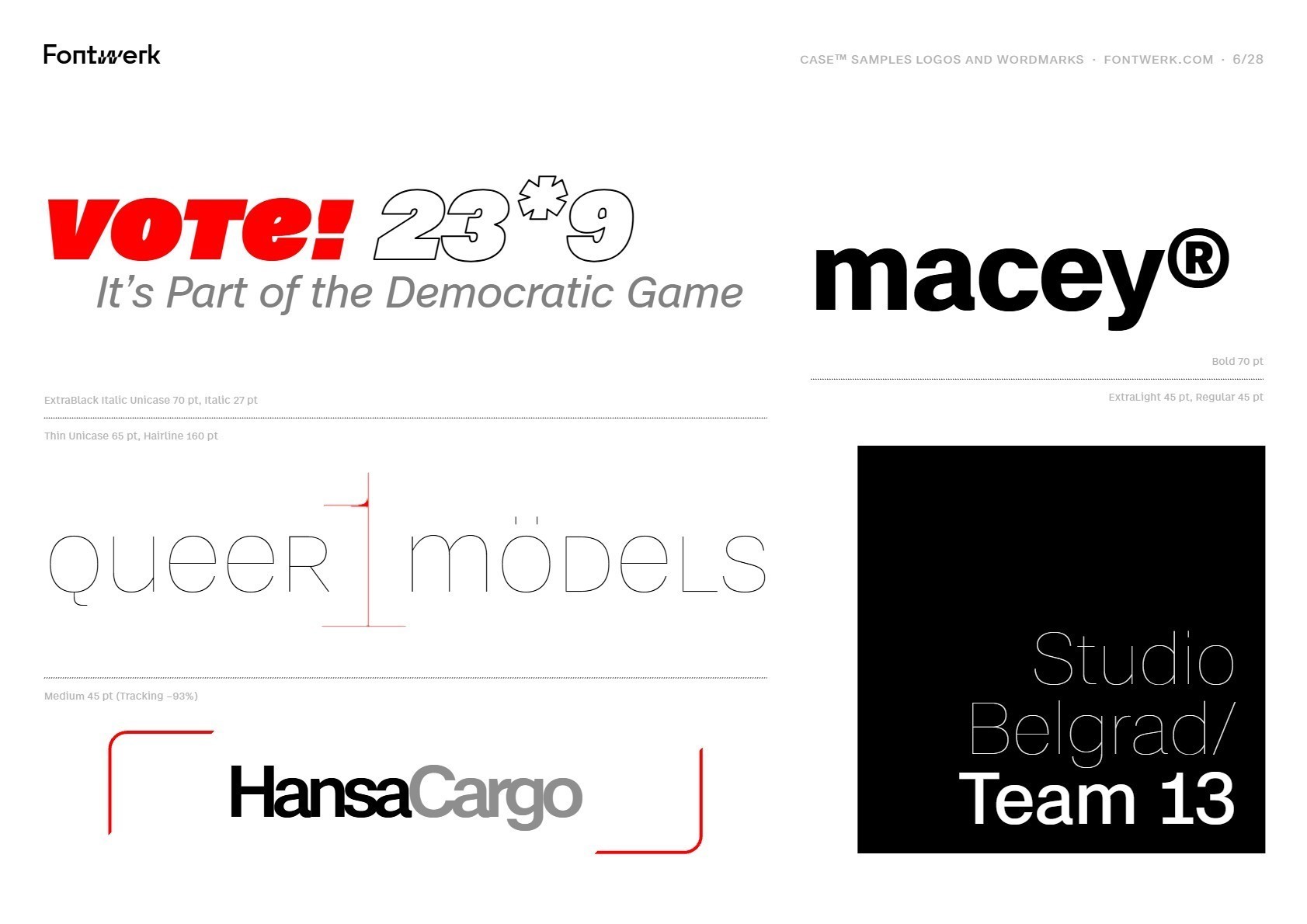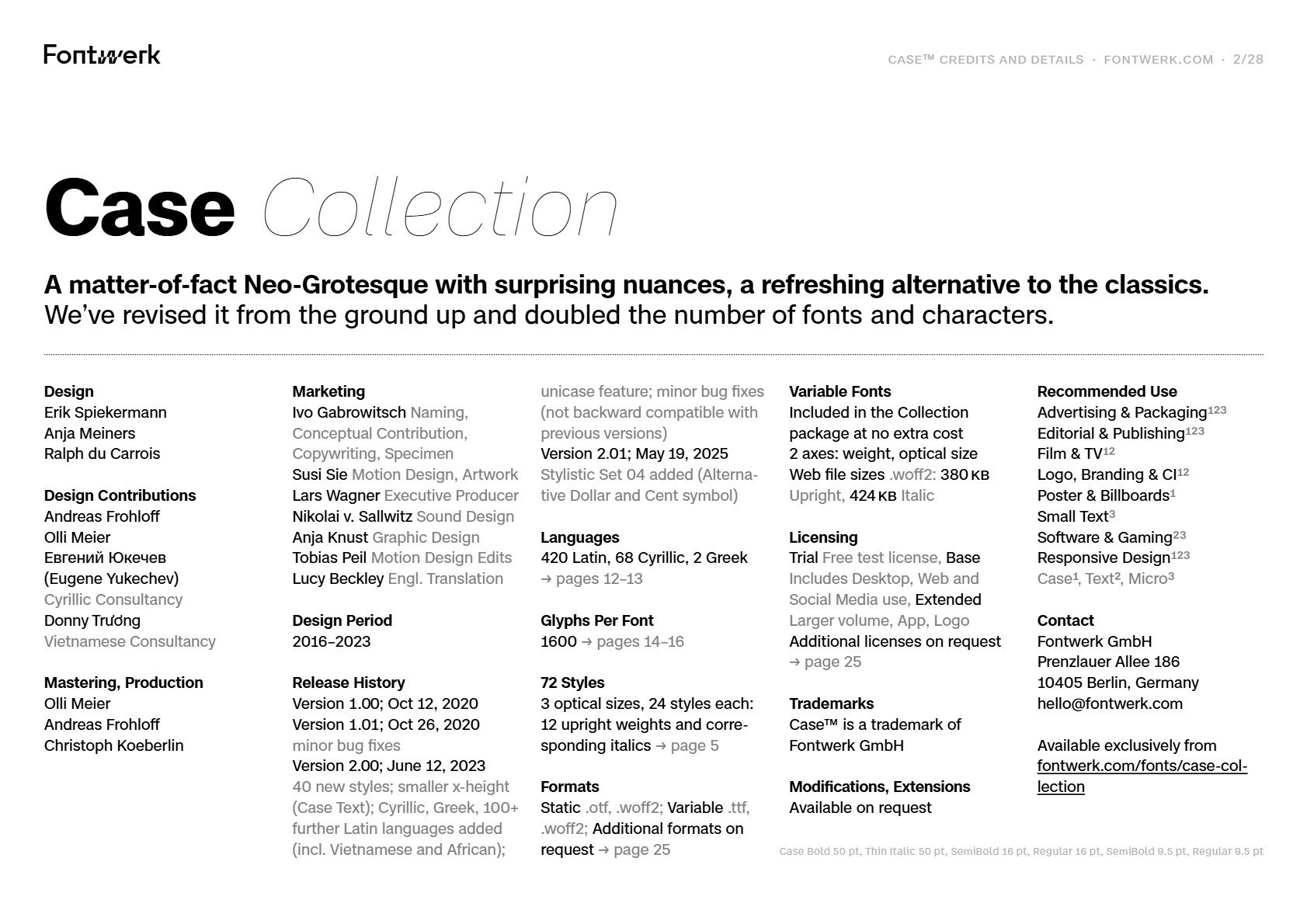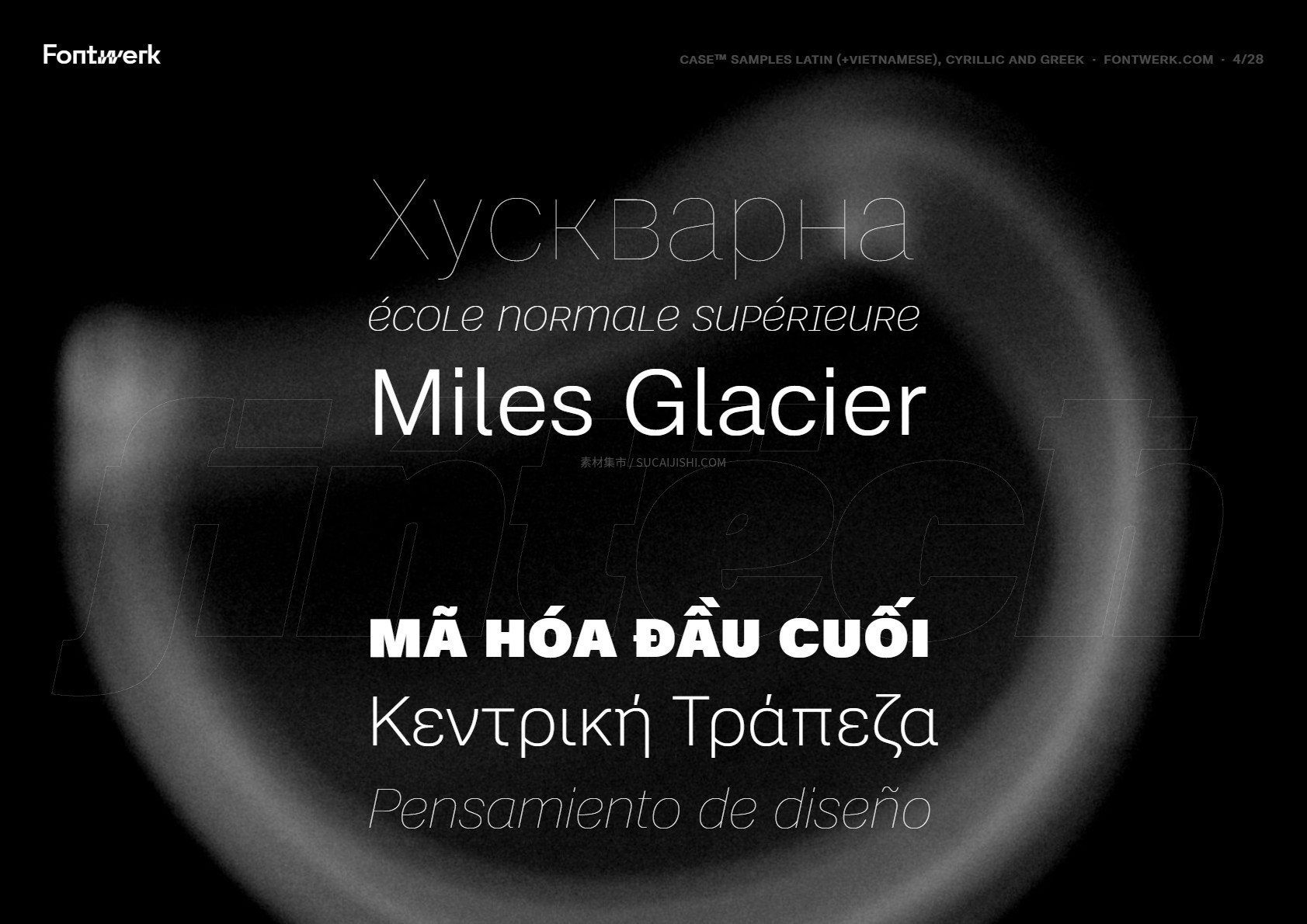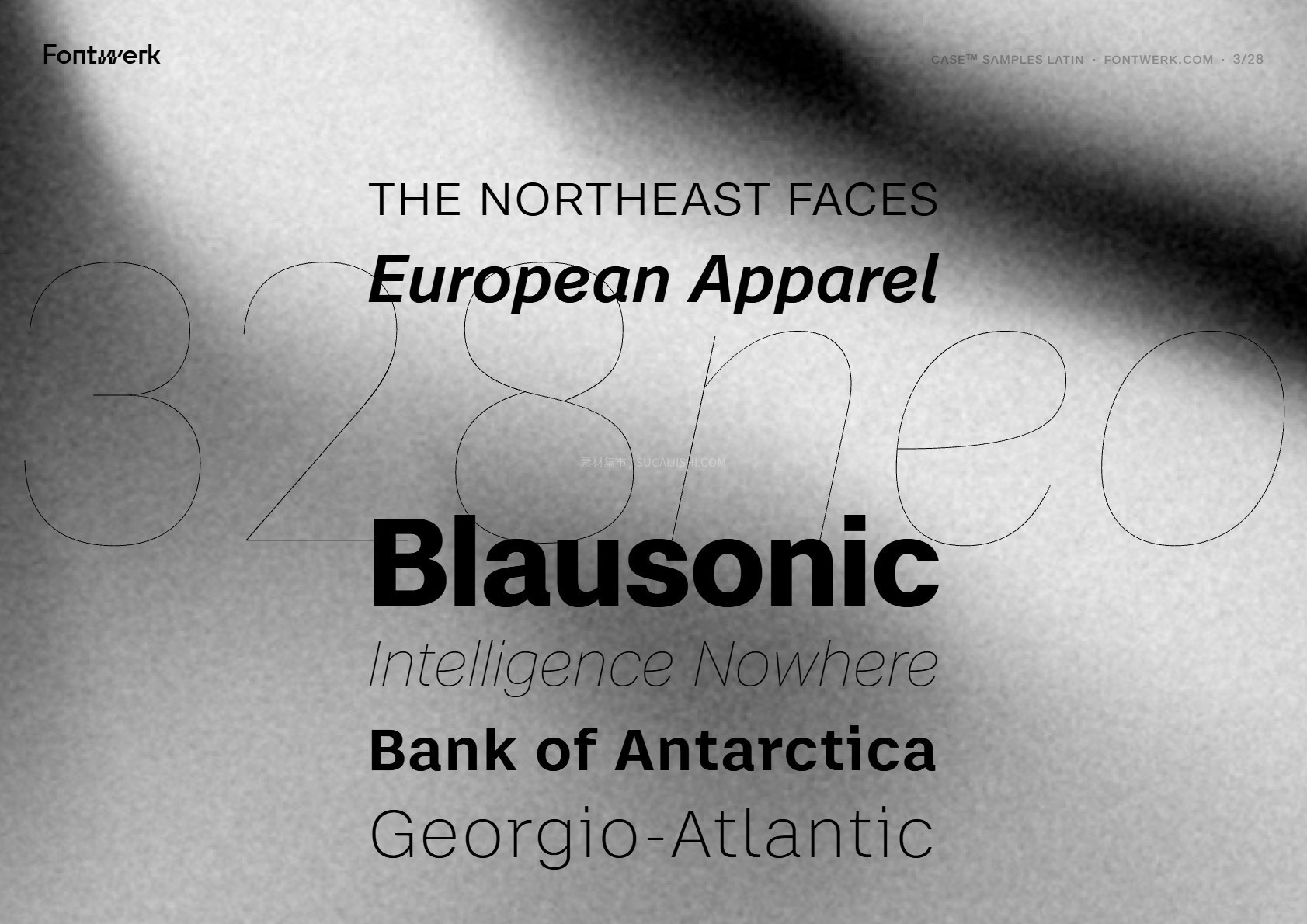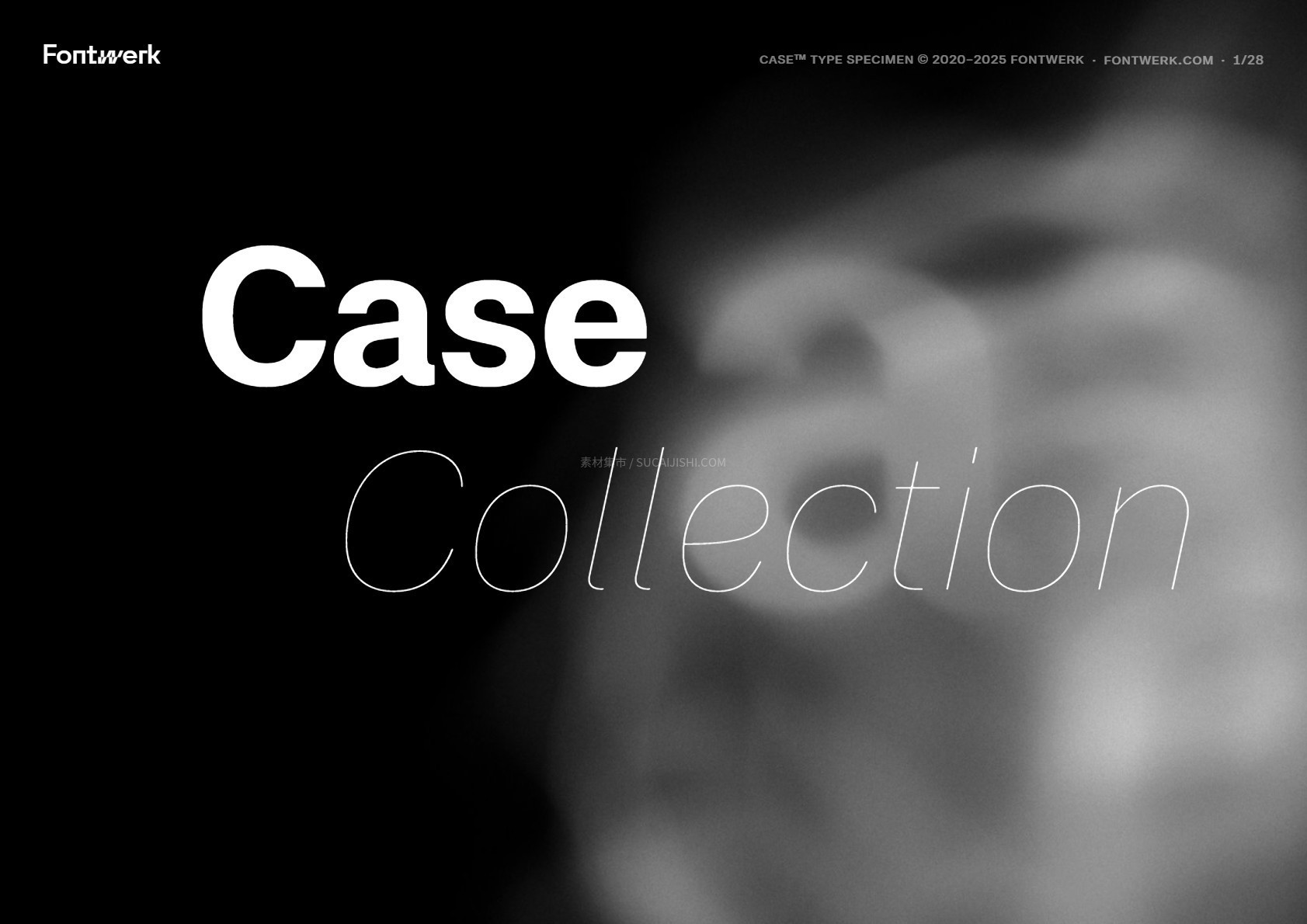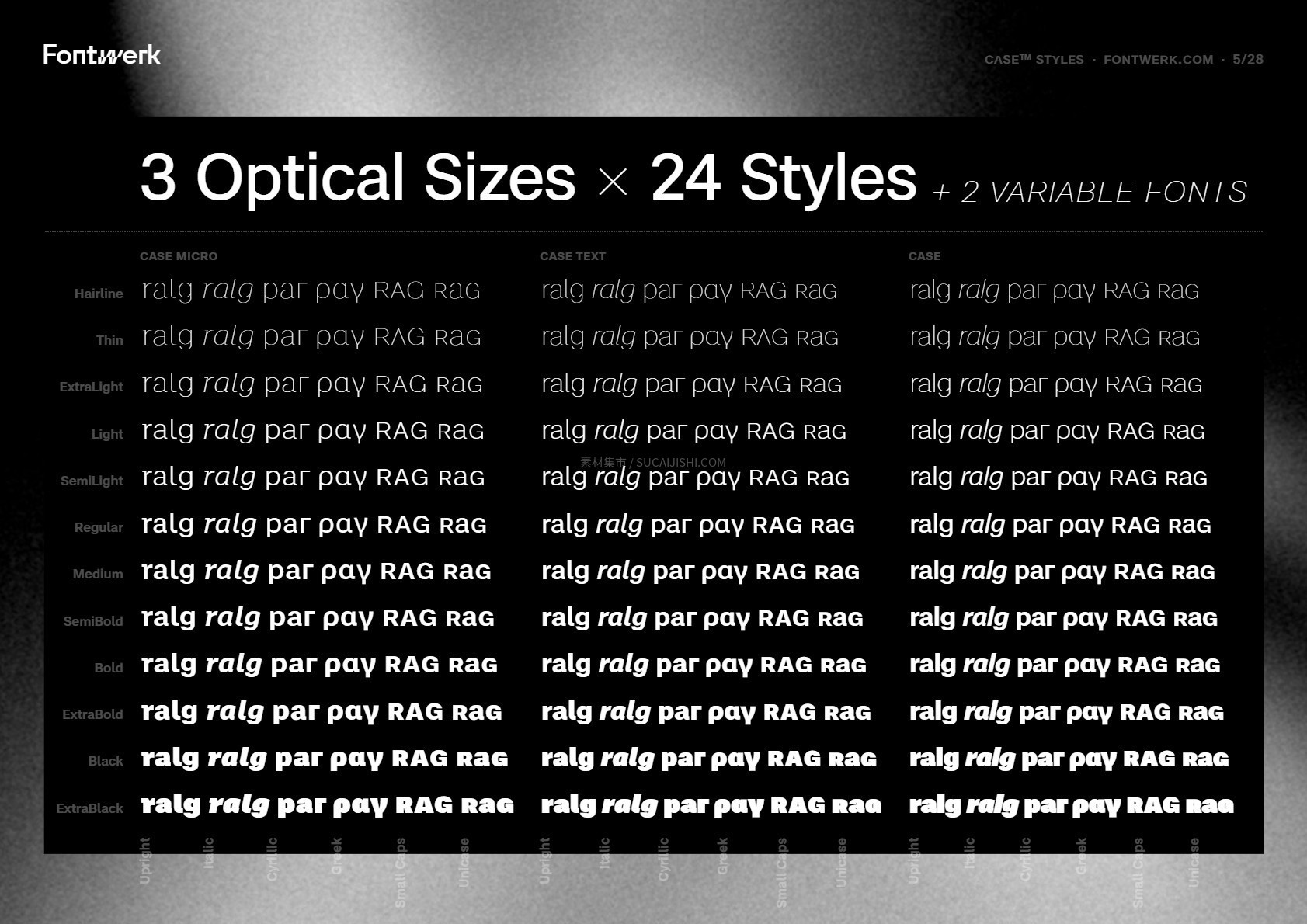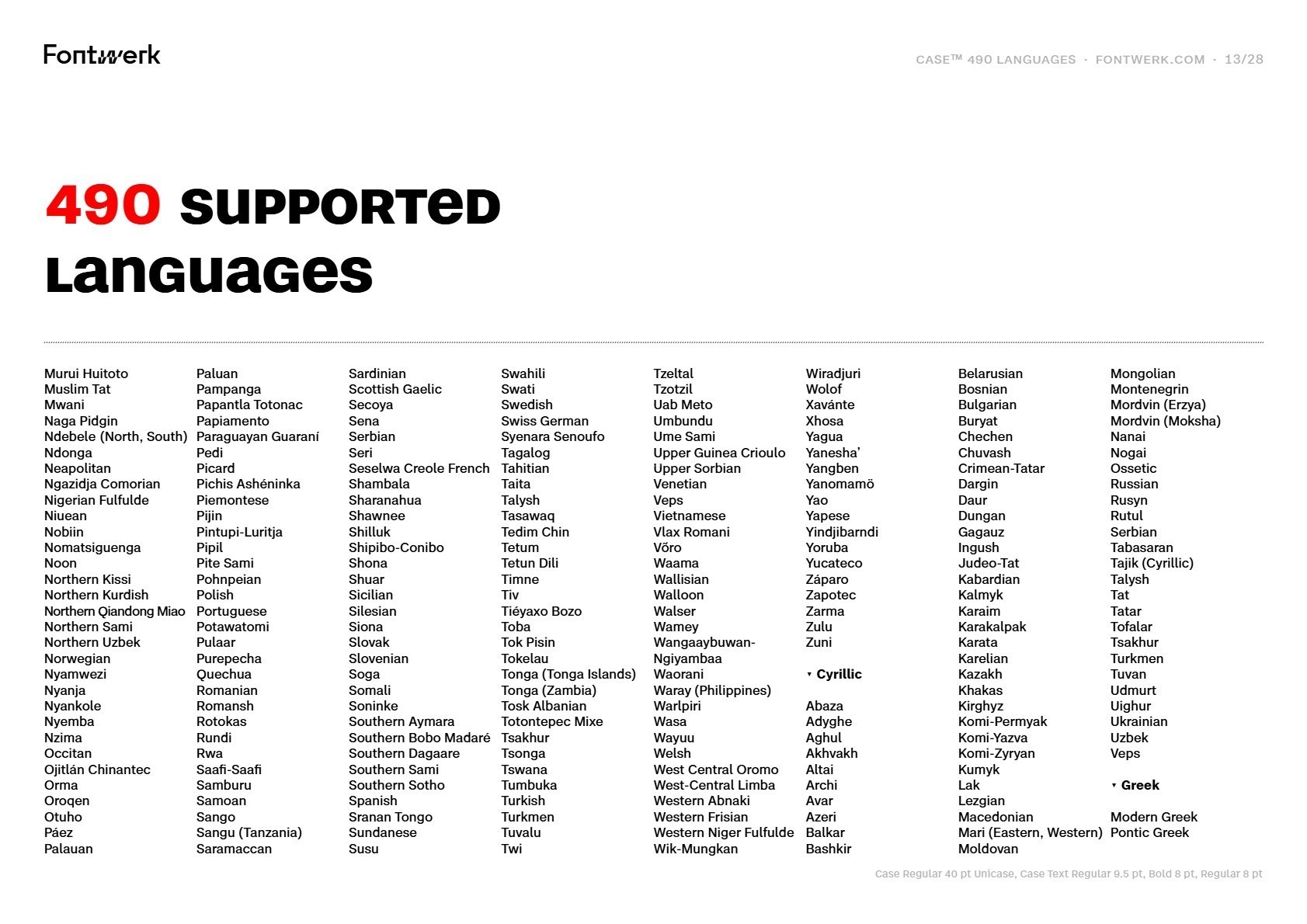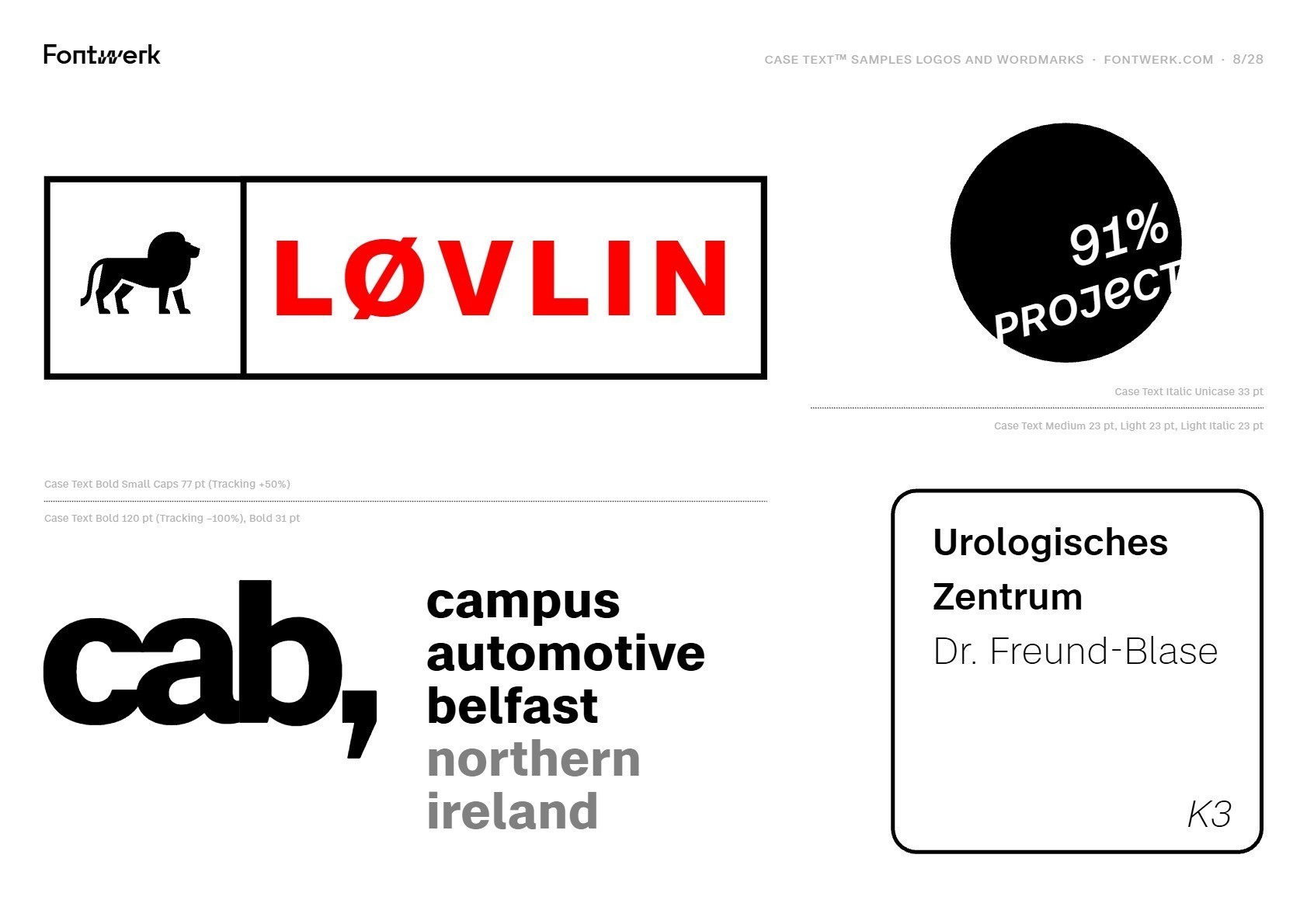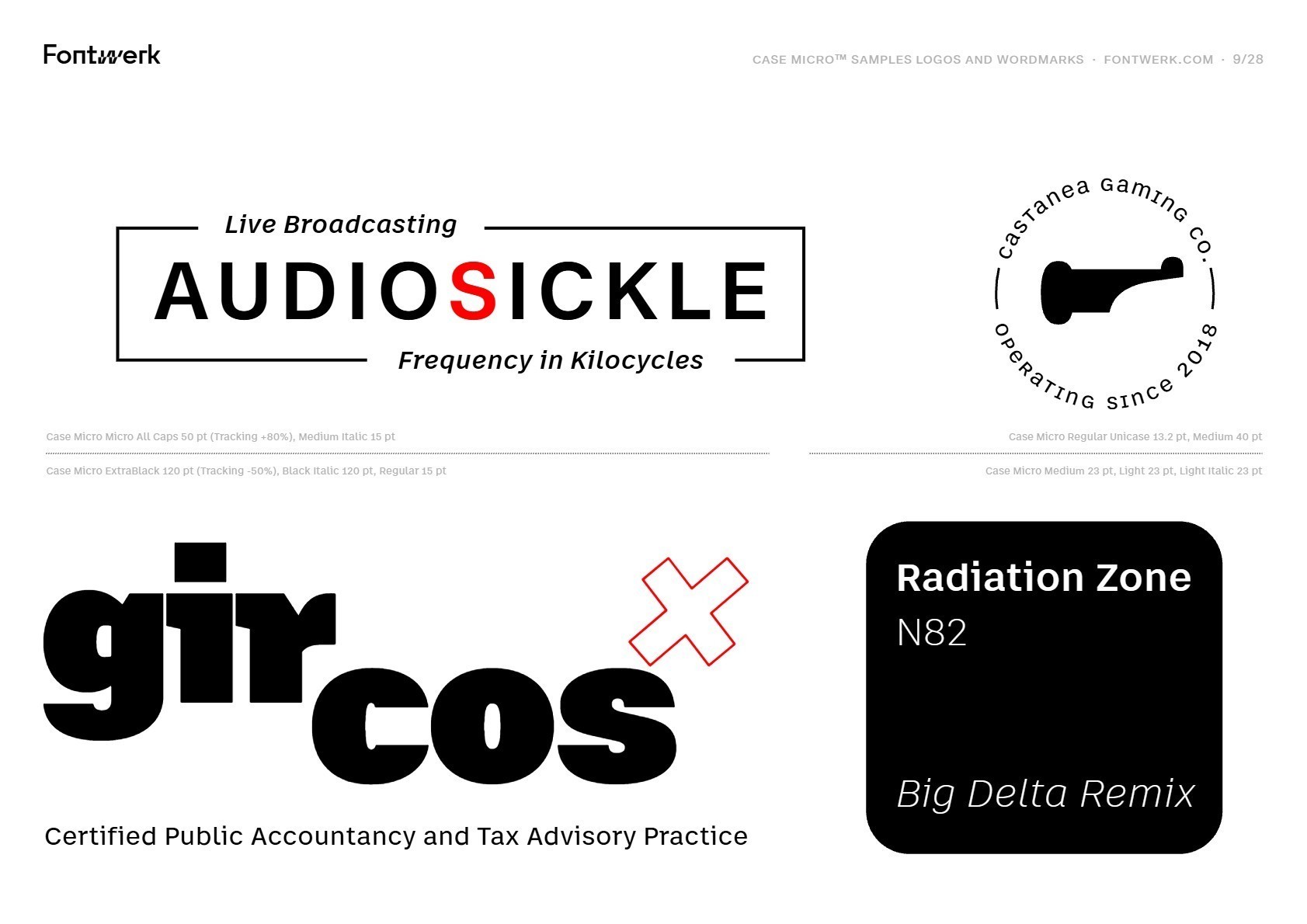
Case Superfamily 现代无衬线字体家族
这套 Case 字体绝对是你应对高端品牌设计的“秘密武器”!它在经典的 Neo-Grotesque 风格基础上注入了极佳的视觉协调性和前瞻性细节。全新 2.0 版本配置拉满,包含高达 72 种样式,外加 2 款超灵活的可变字体!自带三种光学字号(核心、Text、Micro),无论是巨幅海报大字,还是 4pt 的微型屏幕脚注,都能保持极致清晰锐利。再搭配罕见的精美“真实斜体”与 UniCASE 统一大小写玩法,全面支持西里尔、希腊等多国语言,帮你轻松拿捏各种复杂的跨屏幕、跨平台排版需求!
字体太有锋芒了,只适合特定主题,一般的企业商务画册根本压不住这种气场。